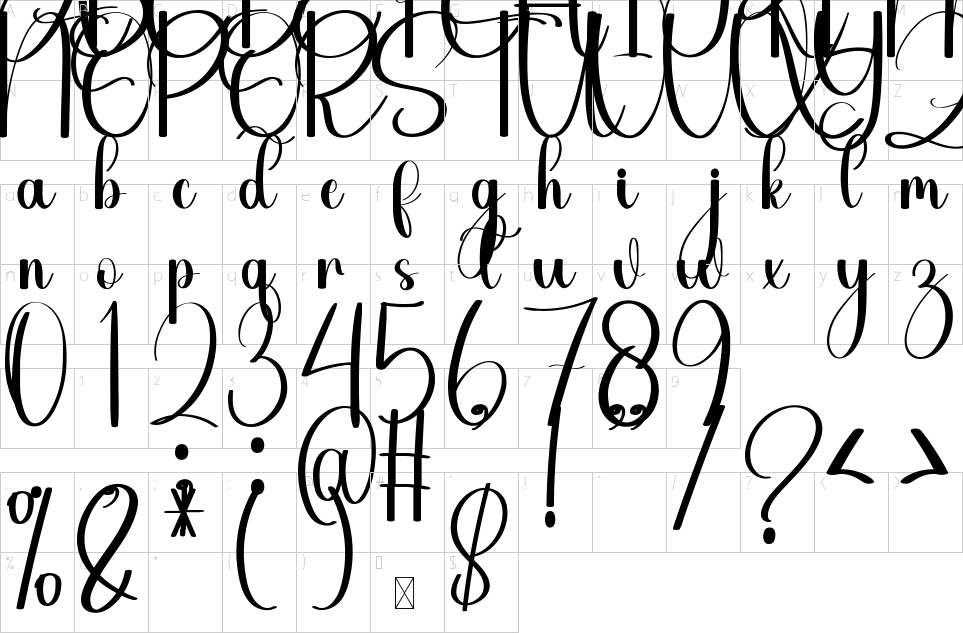
A Dragonfly é uma elegante e versátil fonte que se destaca entre as muitas opções disponíveis no mercado. Arquitetada pela InermediaSTUDIO, essa fonte foi criada para trazer um toque único aos projetos digitais, seja em desktop Windows ou Mac. Suavemente arredondada com traços leves, a Dragonfly é uma escolha adequada tanto para textos legíveis quanto para efeitos gráficos inovadores. Com seu design cuidadosamente pensado, ela oferece um conjunto completo de caracteres que abrange letras maiúsculas e minúsculas, números e símbolos. Se você está buscando uma fonte comum mas moderna e elegante para seus projetos digitais, a Dragonfly é uma ótima opção. Descubra por si mesmo como esta fonte pode dar um toque especial aos seus documentos, sites ou qualquer outro projeto que precise de um ar sofisticado. Clique no botão de download agora e experimente essa fonte gratuita para Windows e Mac hoje!